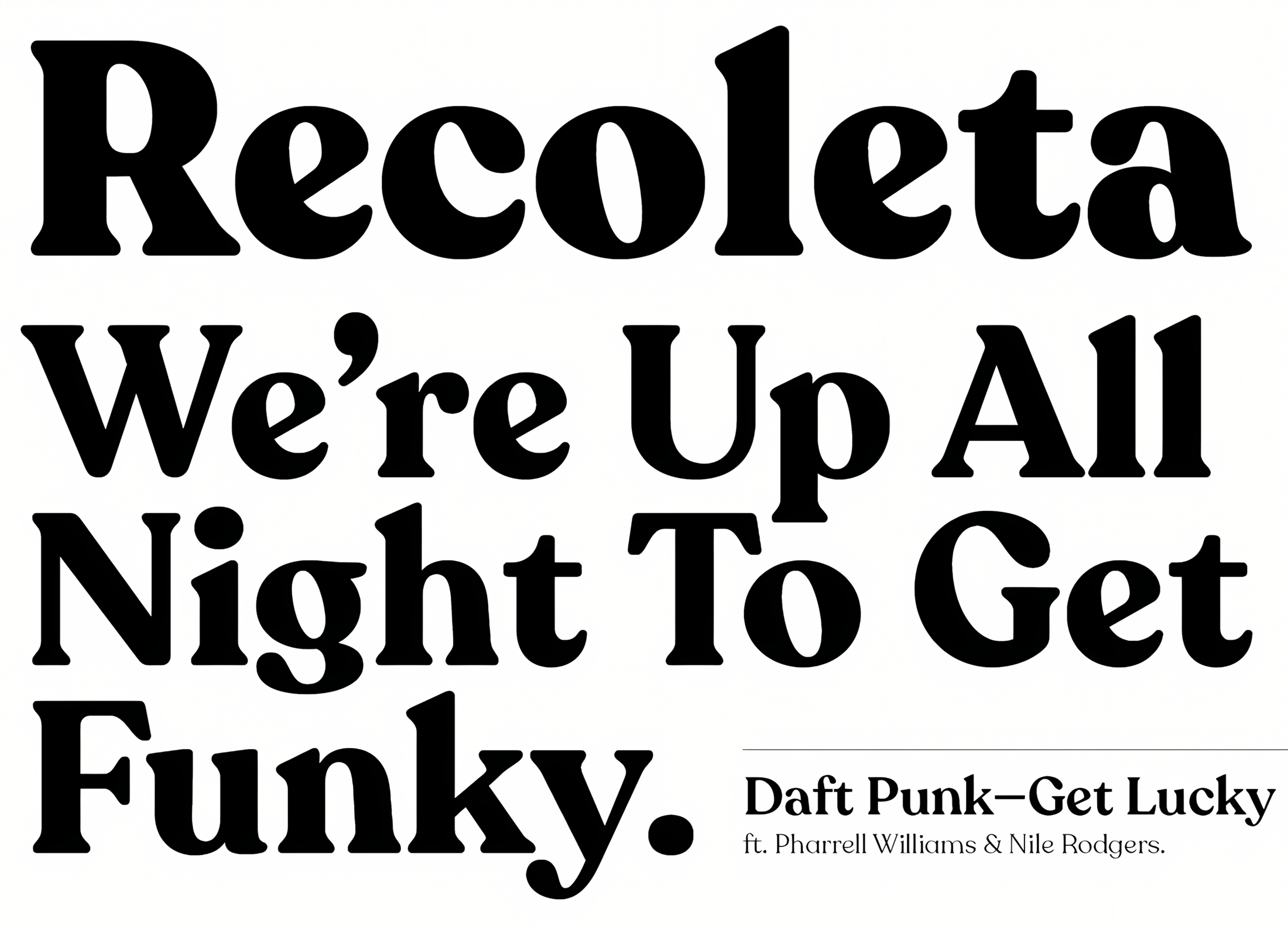
| Descripción | Al igual que la receta de la abuela, Recoleta combina una variedad de ingredientes -de varios tipos de letra populares de los años setenta, como las formas suaves y delicadas de Cooper o los trazos fluidos y angulosos de Windsor- mezclados en un único diseño que presenta sabores familiares, pero frescos y modernos. Su variedad de pesos proporciona una gama de opciones que le ayudarán a encontrar el mejor color tipográfico para su proyecto. Los pesos más ligeros son adecuados para el cuerpo de texto, mientras que los más pesados son ideales para titulares de gran impacto. Las alternativas estilísticas disponibles ofrecen una serie de caracteres diferentes que darán a su logotipo o tarjeta de visita un aspecto único. |
| Familia(s) | Recoleta |